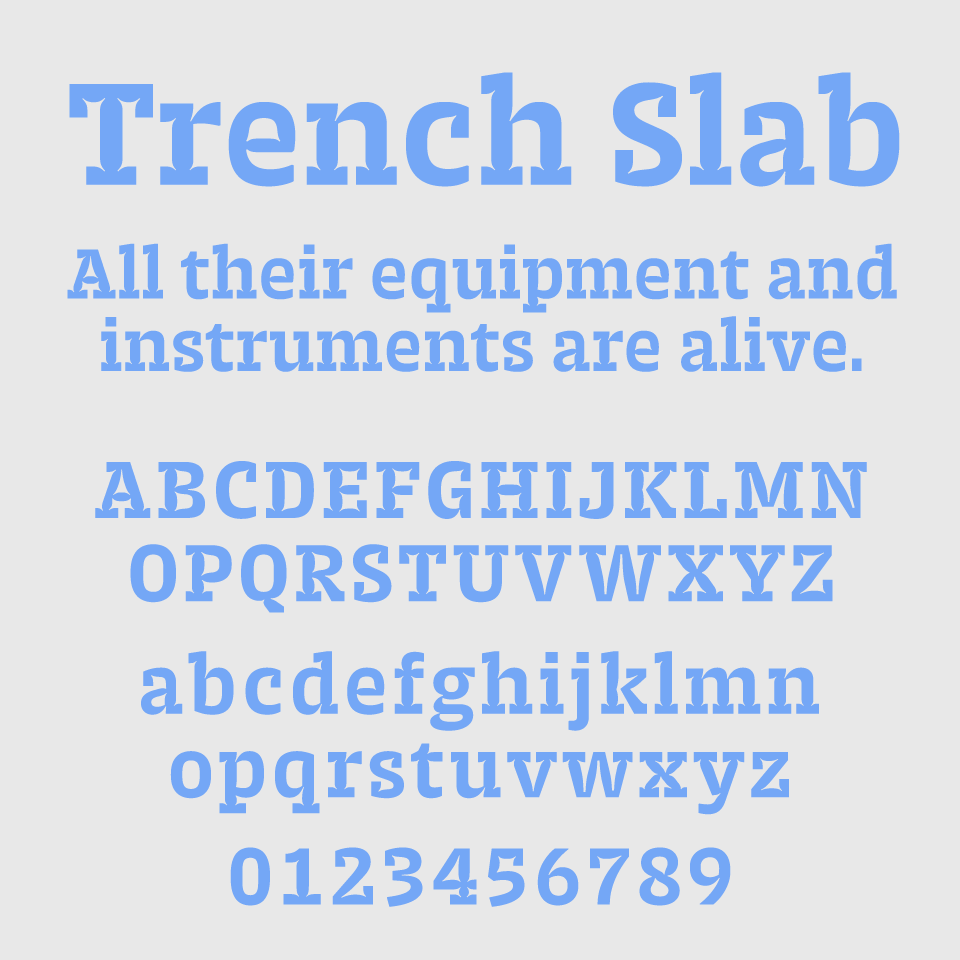
Trench Slab Fontフォントは、骨太なセリフとすっきりした文字幅と、ユニークな切り込みが特徴で、クラシカルながらも現代的な整然さを感じさせるスラブセリフフォントです。
ちょっとレトロな風合いを感じるので、新聞の見出しやポスター、雑誌のタイトルなどにもなじむ安定感があり、情報伝達とデザイン性の両立ができる印象です。ヴィンテージ感と実用性を両方備えた、使い勝手の良いフォントです。